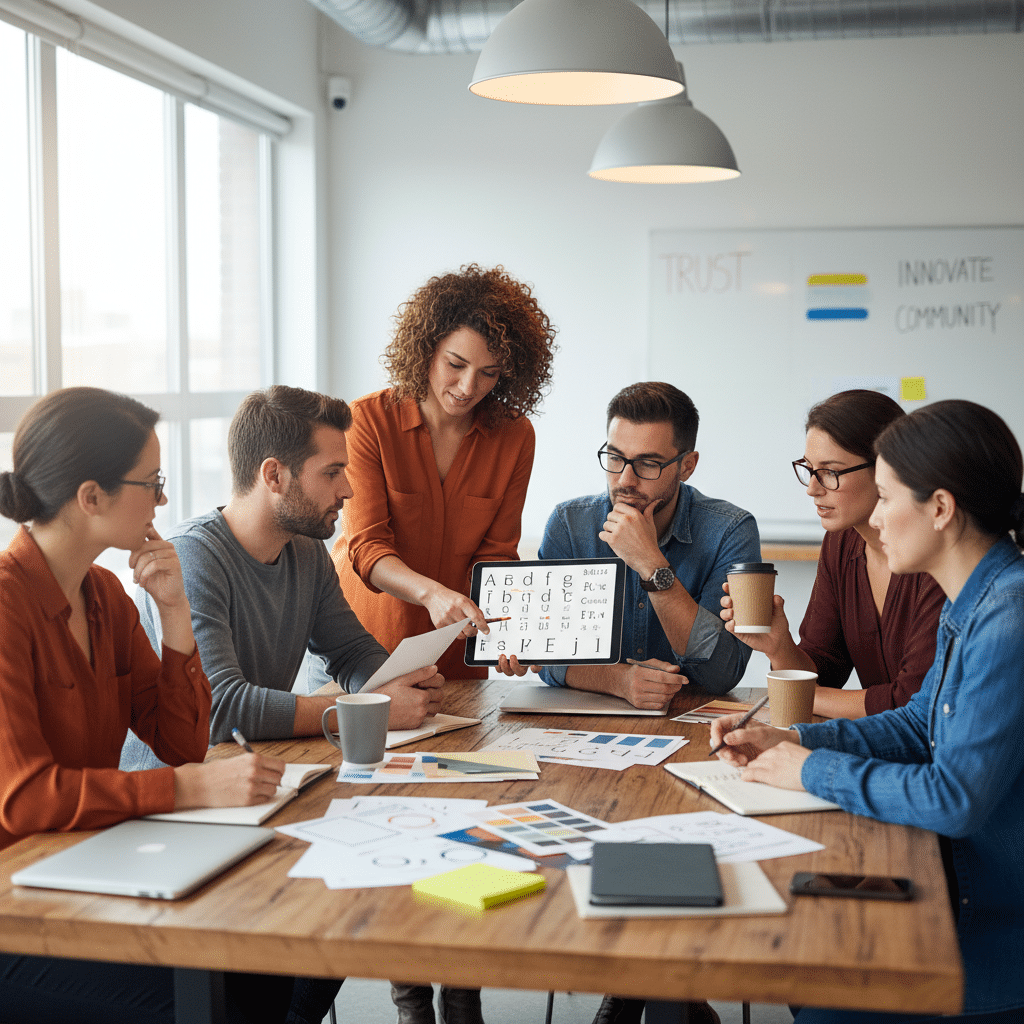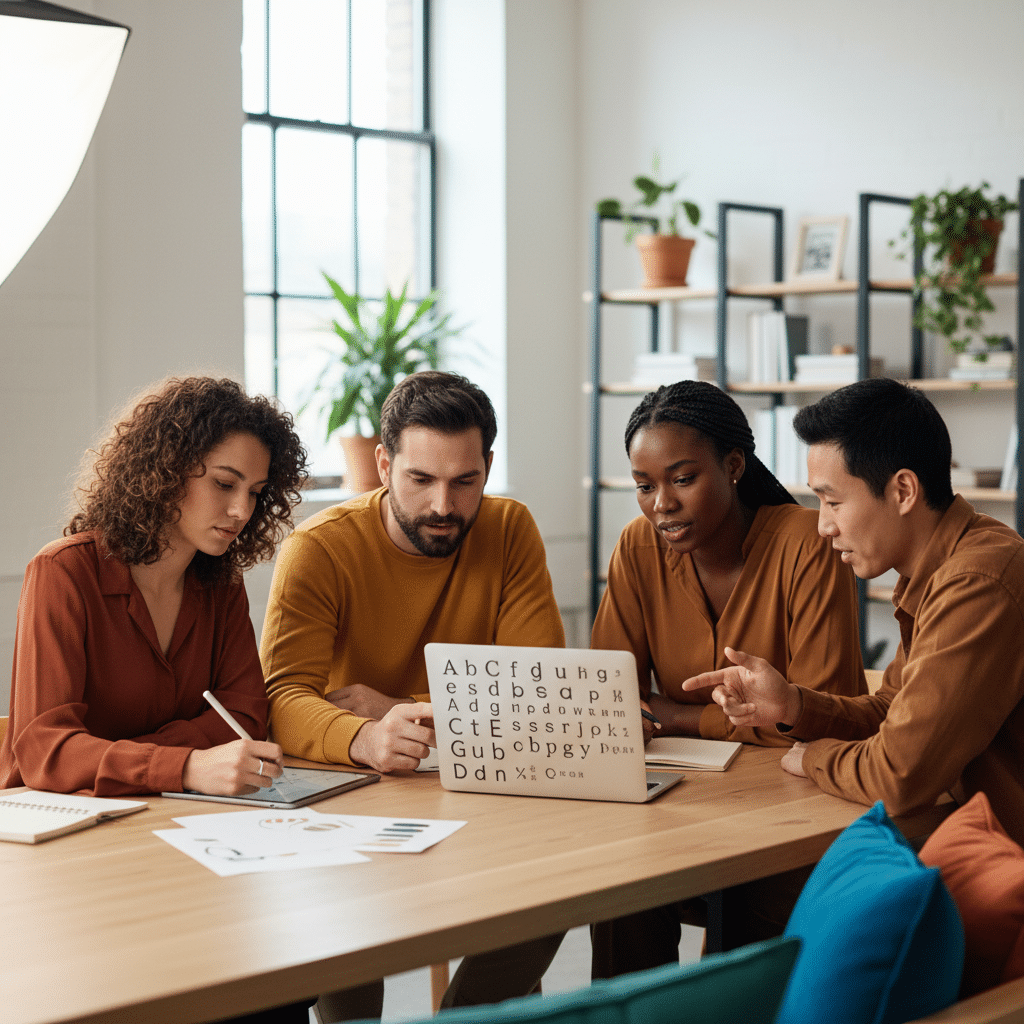
ฟอนต์มีผล! เลือกฟอนต์สร้างแบรนด์ SME ยังไงให้ปัง
การเลือกแบบอักษรหรือฟอนต์สำหรับธุรกิจขนาดกลางและขนาดย่อม (SME) เป็นมากกว่าการตัดสินใจด้านความสวยงาม แต่เป็นองค์ประกอบเชิงกลยุทธ์ที่สามารถกำหนดการรับรู้และสร้างความสัมพันธ์กับลูกค้าได้ตั้งแต่แรกเห็น ฟอนต์ทำหน้าที่เป็นเสียงและบุคลิกภาพของแบรนด์ โดยสามารถสื่อสารค่านิยม ความน่าเชื่อถือ และอารมณ์ได้อย่างทรงพลัง
หัวใจของการเลือกฟอนต์สำหรับธุรกิจ SME
- สื่อสารบุคลิกภาพแบรนด์: ฟอนต์ที่เลือกใช้ควรสะท้อนตัวตนของแบรนด์ได้อย่างชัดเจน ไม่ว่าจะเป็นความน่าเชื่อถือ ความทันสมัย ความหรูหรา หรือความเป็นกันเอง
- ความชัดเจนในการสื่อสาร: ฟอนต์ที่ดีต้องอ่านง่ายในทุกขนาดและบนทุกสื่อ ตั้งแต่โลโก้บนนามบัตรไปจนถึงเนื้อหาบนเว็บไซต์และบรรจุภัณฑ์สินค้า
- สร้างการจดจำและความแตกต่าง: การเลือกฟอนต์ที่มีเอกลักษณ์และสอดคล้องกับแบรนด์ ช่วยให้ธุรกิจโดดเด่นจากคู่แข่งและเป็นที่จดจำในใจของผู้บริโภคได้ง่ายขึ้น
- สร้างความน่าเชื่อถือ: ฟอนต์ที่ดูเป็นมืออาชีพและสม่ำเสมอในการสื่อสารทุกช่องทาง ช่วยสร้างความไว้วางใจและความเชื่อมั่นในคุณภาพของสินค้าและบริการ
- ความสอดคล้องคือกุญแจสำคัญ: การกำหนดฟอนต์หลักสำหรับหัวข้อและเนื้อหา (ประมาณ 1-2 แบบ) และใช้งานอย่างสม่ำเสมอ จะช่วยสร้างภาพลักษณ์แบรนด์ที่แข็งแกร่งและเป็นระบบ
บทความนี้จะสำรวจประเด็นว่าทำไมฟอนต์มีผล! เลือกฟอนต์สร้างแบรนด์ SME ยังไงให้ปัง โดยจะเจาะลึกถึงหลักการทางจิตวิทยาของฟอนต์แต่ละประเภท พร้อมนำเสนอแนวทางปฏิบัติที่ชัดเจนสำหรับผู้ประกอบการ SME ในการเลือกใช้ตัวอักษรเพื่อสร้างแบรนด์ให้ประสบความสำเร็จและเป็นที่จดจำในตลาดที่มีการแข่งขันสูง
ทำไมการเลือกฟอนต์จึงเป็นองค์ประกอบสำคัญในการสร้างแบรนด์
ในโลกธุรกิจที่ภาพลักษณ์คือสิ่งแรกที่ลูกค้าสัมผัส การเลือกฟอนต์จึงมีความสำคัญเทียบเท่ากับการออกแบบโลโก้หรือการเลือกสีประจำแบรนด์ ฟอนต์เปรียบเสมือน “เสื้อผ้า” ที่แบรนด์สวมใส่ หรือ “น้ำเสียง” ที่ใช้ในการสื่อสารกับลูกค้า มันสามารถกำหนดโทนและอารมณ์ของการสื่อสารทั้งหมดได้ในทันที แบรนด์ที่เกี่ยวข้องกับการเงินหรือกฎหมายอาจเลือกใช้ฟอนต์ที่ดูมั่นคง จริงจัง และน่าเชื่อถือ เพื่อสร้างความไว้วางใจ ในขณะที่ร้านกาแฟหรือแบรนด์เสื้อผ้าสำหรับเด็กอาจเลือกใช้ฟอนต์ที่ดูเป็นกันเอง อบอุ่น และเข้าถึงง่าย เพื่อสร้างความรู้สึกที่ดี
สำหรับธุรกิจ SME ที่อาจมีงบประมาณจำกัดในการสร้างแบรนด์ การเลือกฟอนต์ที่เหมาะสมถือเป็นการลงทุนที่คุ้มค่าอย่างยิ่ง เพราะมันเป็นเครื่องมือที่ทรงพลังในการสร้างการจดจำ เมื่อลูกค้าเห็นฟอนต์ลักษณะเดิมซ้ำๆ ในทุกช่องทางการสื่อสาร ไม่ว่าจะเป็นบนโซเชียลมีเดีย บรรจุภัณฑ์ หรือหน้าร้าน จะเกิดการเชื่อมโยงระหว่างรูปแบบตัวอักษรนั้นกับแบรนด์โดยอัตโนมัติ สิ่งนี้ช่วยเสริมสร้างเอกลักษณ์ของแบรนด์ให้แข็งแกร่งและทำให้ลูกค้าสามารถระบุตัวตนของแบรนด์ท่ามกลางคู่แข่งมากมายได้อย่างรวดเร็ว นอกจากนี้ ฟอนต์ที่สอดคล้องกับบุคลิกของแบรนด์และกลุ่มเป้าหมายยังช่วยให้แบรนด์สามารถสื่อสารคุณค่าและความจริงใจได้อย่างมีประสิทธิภาพ ทำให้ลูกค้ารู้สึกว่าแบรนด์มีความเป็นมืออาชีพและใส่ใจในรายละเอียด
เจาะลึกจิตวิทยาฟอนต์: ศาสตร์แห่งการสื่อสารผ่านตัวอักษร
การเลือกฟอนต์ไม่ใช่เรื่องของความชอบส่วนตัว แต่เป็นกระบวนการที่ต้องอาศัยความเข้าใจในหลักจิตวิทยา หรือที่เรียกว่า Font Psychology ฟอนต์แต่ละประเภทมีโครงสร้างและลักษณะเฉพาะตัวที่สามารถกระตุ้นการรับรู้และอารมณ์ที่แตกต่างกันในสมองของมนุษย์ การทำความเข้าใจความหมายที่ซ่อนอยู่เบื้องหลังฟอนต์แต่ละรูปแบบ จะช่วยให้ผู้ประกอบการ SME สามารถเลือกเครื่องมือสื่อสารที่ตรงกับเป้าหมายของแบรนด์ได้มากที่สุด
ฟอนต์มีเชิง (Serif): ความคลาสสิกและความน่าเชื่อถือ
ฟอนต์ประเภท Serif มีลักษณะเด่นคือมี “เชิง” หรือขีดเล็กๆ ที่ปลายของตัวอักษร ซึ่งเป็นรูปแบบที่มีประวัติศาสตร์ยาวนาน ย้อนไปถึงยุคโรมัน ทำให้ฟอนต์ประเภทนี้มักให้ความรู้สึกถึงความคลาสสิก ประเพณีนิยม ความน่าเชื่อถือ และความเป็นทางการ แบรนด์ที่ต้องการสร้างภาพลักษณ์ที่ดูมั่นคง มีเกียรติ และไว้วางใจได้ มักนิยมใช้ฟอนต์ Serif ตัวอย่างเช่น สถาบันการเงิน สำนักพิมพ์ สำนักงานกฎหมาย หรือแบรนด์สินค้าหรูหราที่ต้องการเน้นย้ำถึงประวัติศาสตร์และคุณภาพที่สืบทอดกันมานาน การศึกษาบางชิ้นยังชี้ให้เห็นว่าฟอนต์อย่าง Cotford Serif สามารถเพิ่มการรับรู้ถึงความหรูหราและความน่าเชื่อถือให้กับผลิตภัณฑ์ได้จริง
ฟอนต์ไม่มีเชิง (Sans-serif): ความทันสมัยและความเรียบง่าย
ตรงกันข้ามกับ Serif ฟอนต์ประเภท Sans-serif (Sans แปลว่า “ไม่มี” ในภาษาฝรั่งเศส) คือฟอนต์ที่ไม่มีเชิงที่ปลายตัวอักษร ทำให้มีรูปลักษณ์ที่ดูสะอาดตา เรียบง่าย และทันสมัย ฟอนต์กลุ่มนี้ได้รับความนิยมอย่างสูงในยุคดิจิทัล เนื่องจากอ่านง่ายบนหน้าจอคอมพิวเตอร์และสมาร์ทโฟน แบรนด์ที่ต้องการสื่อสารถึงความทันสมัย นวัตกรรม ความตรงไปตรงมา และความเป็นมิตร มักเลือกใช้ฟอนต์ Sans-serif เหมาะสำหรับธุรกิจเทคโนโลยี สตาร์ทอัพ แบรนด์แฟชั่นมินิมอล หรือธุรกิจที่ต้องการเข้าถึงกลุ่มคนรุ่นใหม่ที่ชื่นชอบความเรียบง่ายและชัดเจน
ฟอนต์ลายมือ (Script): ความหรูหราและความเป็นกันเอง
ฟอนต์ประเภท Script หรือฟอนต์ลายมือ มีลักษณะเลียนแบบการเขียนด้วยลายมือ ทำให้มีเส้นสายที่ต่อเนื่องและมีความเป็นศิลปะสูง ฟอนต์กลุ่มนี้สามารถสื่อสารอารมณ์ได้หลากหลาย ตั้งแต่ความหรูหรา สง่างาม และโรแมนติก ไปจนถึงความน่ารัก สดใส และเป็นกันเอง ขึ้นอยู่กับรูปแบบของลายเส้น เหมาะสำหรับแบรนด์ที่ต้องการสร้างความรู้สึกพิเศษและมีเอกลักษณ์เฉพาะตัว เช่น ร้านอาหาร fine-dining แบรนด์เครื่องประดับ การ์ดเชิญงานแต่งงาน หรือร้านค้าที่ขายสินค้าทำมือที่ต้องการเน้นถึงความใส่ใจและมีความเป็นส่วนตัว